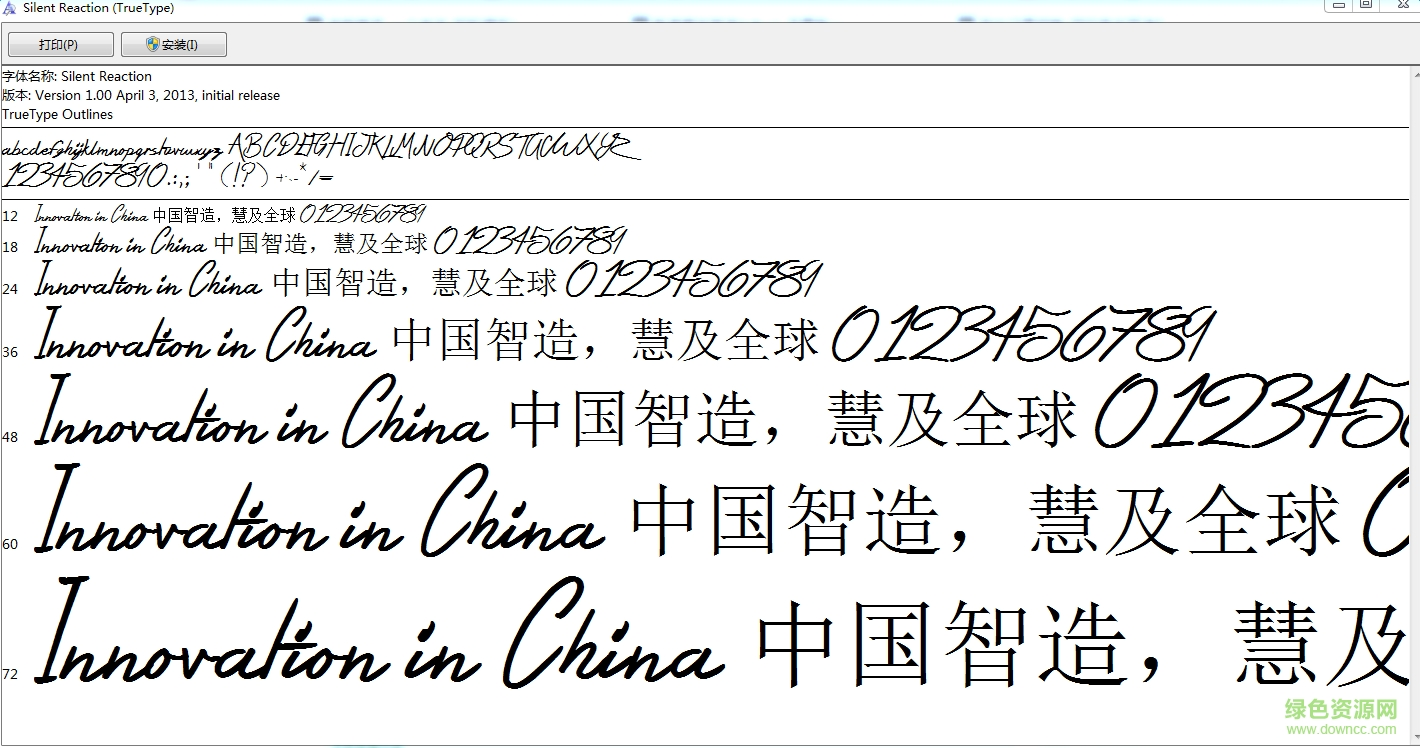
silent reaction英文字體
silent reaction字體是一款手寫風(fēng)格的斜體英文字體,該字體線條飛揚,筆墨超逸,清冽而又優(yōu)雅,感興趣的小伙快來綠色資源網(wǎng)下載吧!
silent reaction字體介紹
silent reaction字體是一款用于美工設(shè)計方面的英文字體,該字體風(fēng)度超逸、墨采飛動、精麗妍美而又自然流便,看上去十分美觀,整體效果非常統(tǒng)一,且字庫完整,可以廣泛應(yīng)用于美術(shù)設(shè)計、廣告設(shè)計、宣傳海報、ppt、影視制作以及任何使用文字的領(lǐng)域,有需要的朋友可以免費下載收藏。